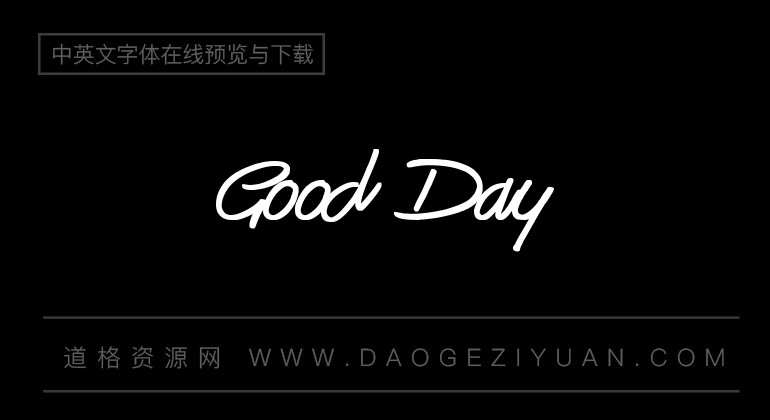
Good Day
? Good Day 是一款简洁优雅的英文字体,由英国设计师 Jeremy Tribby 创作。它的设计理念是简单、清晰、时尚,在字体的细节上使用了细节设计,使字体更加优雅靓丽。它的字体结构清晰,曲线流畅,比例协调,字体的细节细节、线条、曲线都很精细,使它成为一款具有现代感的英文字体。它适用于各种印刷品和电子媒体,可以提供清晰的文字效果,为设计师提供更多的创意空间。
Good Day是一款非常不错的手写艺术字体,具有很好的视觉感,适合于文化类的宣传设计、商业类品牌的广告和产品包装设计以及个性化文字排版等较多场景。